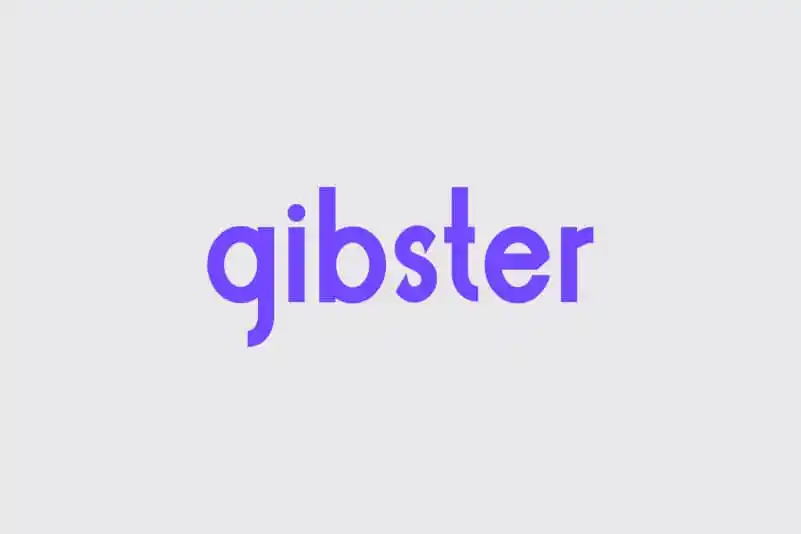
Gibster Sans Serif Font – Fonte Grátis
Gibster Sans Serif Font
A Gibster Sans Serif Font é uma descoberta inédita para amantes da tipografia moderna. Inspirada em uma fusão entre formas geométricas e texturas afiladas, essa fonte de sans-serif traz uma sensação fresca e minimalista que se destaca. Com três versões incríveis – Regular, Italic e Outline – a Gibster apresenta uma harmonia perfeita, complementando mestremente o estilo serifado ou script. Seja para criar logotipos inovadores ou textura sofisticada em projetos de design gráfico, essa fonte é um ótimo aliado. Baixe-a agora e veja por si mesmo como ela pode transformar seus trabalhos!